Trong thế giới thiết kế đồ họa, font chữ cute dễ thương luôn chiếm được cảm tình của nhiều người nhờ vẻ ngoài đáng yêu và sinh động. Các font này thường có những đường nét tròn trịa, mềm mại, thường được sử dụng trong các sản phẩm dành cho trẻ em, thiệp mời, hoặc các thiết kế liên quan đến lễ hội. Sự phong phú của các kiểu chữ từ viết tay đến đồ họa, mang đến khả năng thích ứng cao với nhiều loại hình ứng dụng sáng tạo khác nhau.
ToggleFont chữ cute dễ thương: Font VNI – Truck
Font chữ dễ thương: iCiel Pony Font
Font chữ dễ thương việt hóa độc đáo: Frankfurter Bold Font
Font chữ cute dễ thương viết tay: HaloHandletter Font
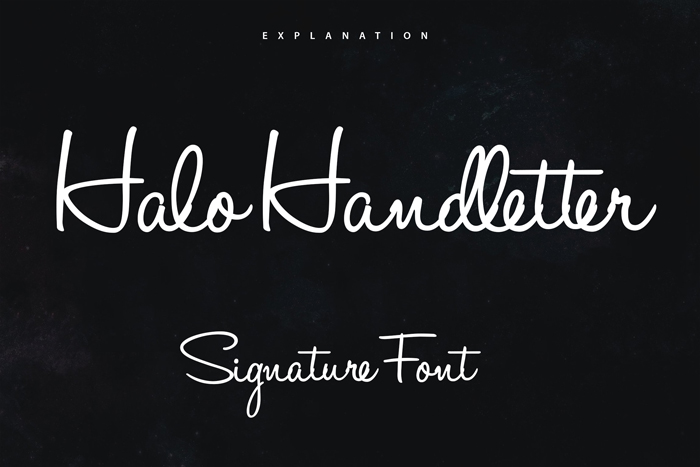
Font chữ dễ thương có chân: Font MTD Esther
Font cute dễ thương script: MTD Beautiful Friends
Font chữ cute dễ thương nét tròn: Font Agbalumo
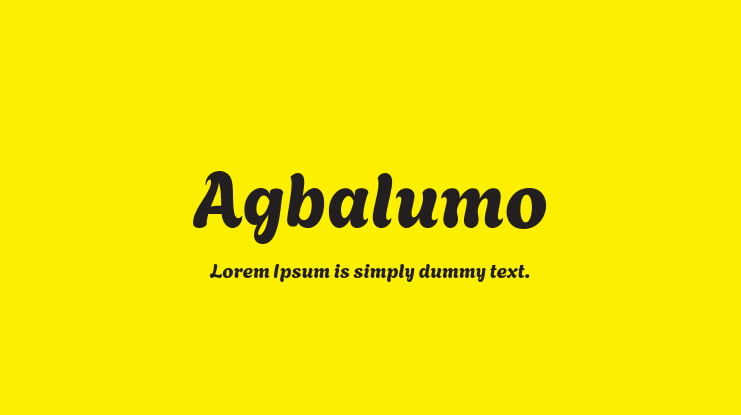
Font nét mảnh dễ thương: Font HLT RollingPen
Font cute việt hóa: Morning Miow
Font việt hóa dễ thương: iCiel Be Cool